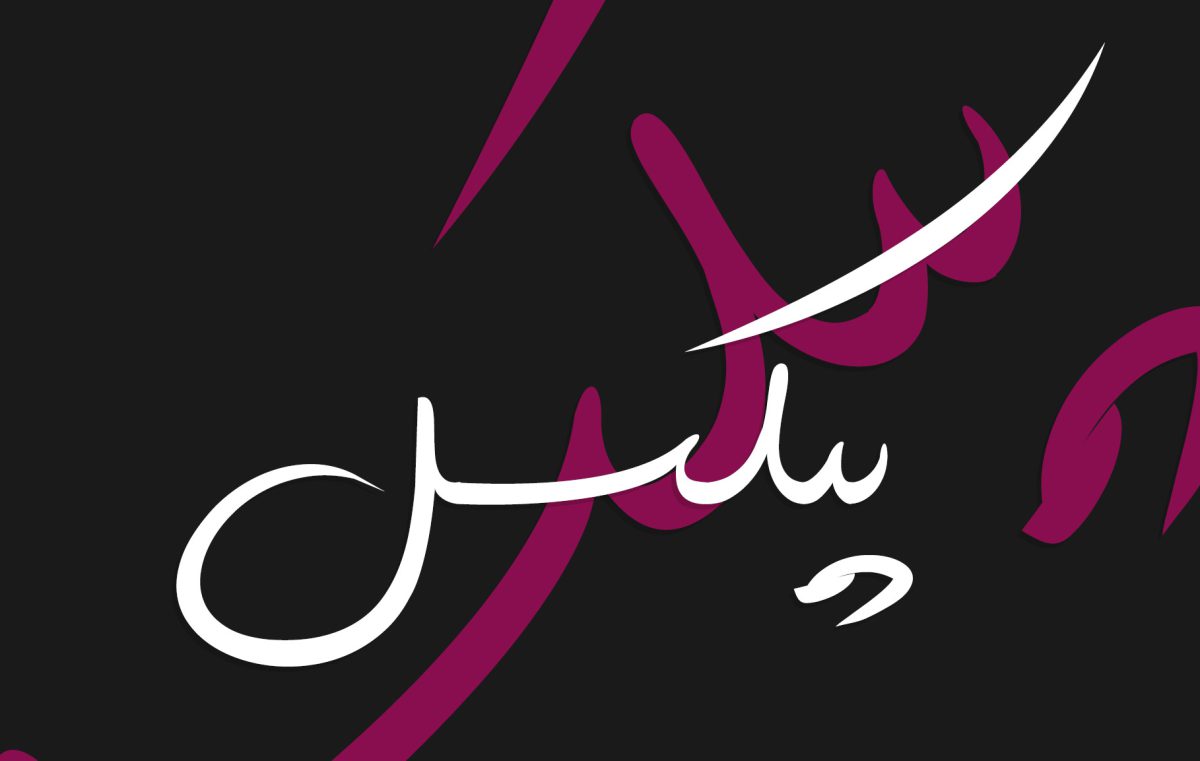
2 فونت تحریری فارسی Tahriri
فونت تحریری دست نویس، یکی از زیباترین قلم های دست نویس با سبک خودکار روان است که با حروف بسیار نرم، کشیده و زیبا طراحی شده است. این فونت حرفه ای شامل حروف انگلیسی و فارسی و اعداد متناسب، هر دو به حالت دست نویس و خوشنویسی، می باشد. فونت تحریری به طراحان و کاربران امکان می دهد بدون نیاز به قلم نوری یا دانش خوشنویسی، طرح هایی با سبک تحریری و دست نویس خلق کنند. این قلم زیبا با فرمت TTF طراحی شده، قابل نصب و استفاده در تمامی برنامه ها (ویندوز و موبایل) است و با قیمتی مناسب قابل خریداری می باشد.
مشاهده و دانلودفونت دست نویس تحریری: زیبایی قلم روان برای طراحی های گرافیکی
فونت تحریری دست نویس، یکی از زیباترین قلم های دست نویس است که با الهام از سبک خودکار روان طراحی شده و زیبایی خاصی به متون در محیط های دیجیتال می بخشد. این فونت حرفه ای به صورت حرفه ای و زیبا طراحی و ساخته شده و برای استفاده در انواع طراحی های گرافیکی بسیار مناسب است و جلوه ای شخصی و هنری به کارها اضافه می کند.
ویژگی های بصری اصلی این فونت شامل حروف بسیار نرم، کشیده، و زیبا است. این نرمی و کشیدگی در خطوط، حس جریان و حرکت را منتقل می کند و زیبایی خاص خطوط دست نویس واقعی را بازتاب می دهد. زیبایی این قلم در تصاویر و نمونه های تایپ شده کاملا مشخص و برجسته هستند و در نگاه اول توجه را جلب می کنند. این یک طراحی دست نویس و خاص است که آن را از فونت های ماشینی و خشک متمایز می سازد و حس صمیمیت را القا می کند.
این بسته فونت شامل یک فونت اصلی اپیک تحریری (Epic Tahriri) است که فونت اصلی دست نویس تحریری مورد نظر با تمام ویژگی های شرح داده شده می باشد. همچنین در این بسته، یک فونت با اسم مشابه دیما نستعلیق تحریری نیز قرار داده شده است، اما با تأکید بر اینکه ظاهری کاملا متفاوت از فونت اصلی تحریری دارد و صرفاً ب دلیل کامل بودن آرشیو فونت تحریری در اینجا قرار داده شده است تا مجموعه ای جامع برای کاربران فراهم آید، حتی اگر از نظر بصری با فونت اصلی تفاوت داشته باشد.
دانلودفونت تحریری دست نویس شامل حروف انگلیسی و فارسی هر دو بحالت دستونیس و خوشنویسی است که امکان استفاده در متون دوزبانه و پروژه های بین المللی را فراهم می کند. به طور خاص، دارای تمامی حروف فارسی برای تایپ کامل متون فارسی، حروف انگلیسی متناسب با فونت (به سبک دست نویس و خوشنویسی با روان نویس) برای هماهنگی با متن فارسی، و دارای اعداد فارسی متناسب با فونت می باشد. این مجموعه کامل کاراکتر، آن را برای انواع محتوای فارسی، انگلیسی و ترکیبی کاربردی می سازد و نیازهای مختلف طراحان را پوشش می دهد.
یکی از مهم ترین مزایای این فونت، سهولت استفاده از آن است. طراحان و کاربران می توانند با این قلم زیبا و حرفه ای بدون نیاز به قلم نوری و… و دانش خوشنویسی، بسیار ساده و حرفه ای طرح هایی به صورت تحریری و دست نویس خلق کنند. عدم نیاز به دانش تایپوگرافی در طراحی نیز استفاده از آن را آسان تر می کند؛ زیبایی طراحی آن به گونه ای است که بدون نیاز به تنظیمات پیچیده، نتیجه بصری خوبی حاصل می شود و هر کسی می تواند از آن استفاده کند.
دانلودکاربردهای فونت تحریری دست نویس در طراحی گرافیک
با توجه به سبک دست نویس، حروف بسیار نرم و کشیده، و طراحی حرفه ای، فونت تحریری دست نویس کاربردهای گسترده ای در طراحی گرافیک دارد. این قلم زیبا و حرفه ای مناسب استفاده در انواع طراحی های گرافیکی است. طراحان می توانند با آن طرح هایی به صورت تحریری و دست نویس خلق کنند بدون نیاز به دانش خوشنویسی. مناسب برای عناوین برای جلب توجه با سبکی شخصی، لوگوتایپ (با فرم دست نویس) برای برندهایی با حس صمیمیت، طراحی کارت دعوت برای مناسبت های خاص، گواهینامه ها، پوسترها و المان های بصری با حس شخصی و دست ساز. قابل نصب و استفاده در تمامی برنامه ها چه موبایل و چه ویندوز، امکان بهره گیری از این سبک را در پلتفرم های مختلف فراهم می کند. همچنین برای تایپوگرافی و متون کوتاه که نیاز به جلوه ای هنری دارند، بسیار کاربردی است.